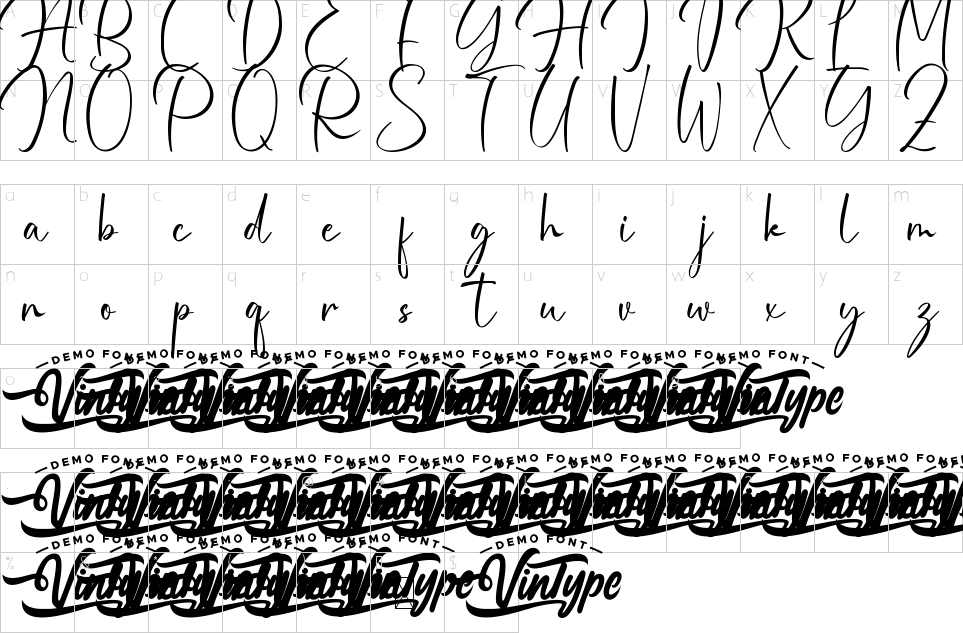
Descubra a fonte ‘Painful Harmony Font’ ao acessar a página de download. Esta elegante fonte é perfeita para quem procura um estilo único e inovador. Desenhada pelo VinType, a ‘Painful Harmony’ é uma escolha excelente para designers e criativos. Esta fonte foi baixada 873 vezes, e já provou seu valor e aprimoramento para diversos projetos de design. Seja para criar um texto impactante ou decorar uma composição de imagem, ‘Painful Harmony’ é uma escolha sólida. Experimente hoje e descubra por si mesmo o poder desta fonte, disponível gratuitamente para Windows e Mac.